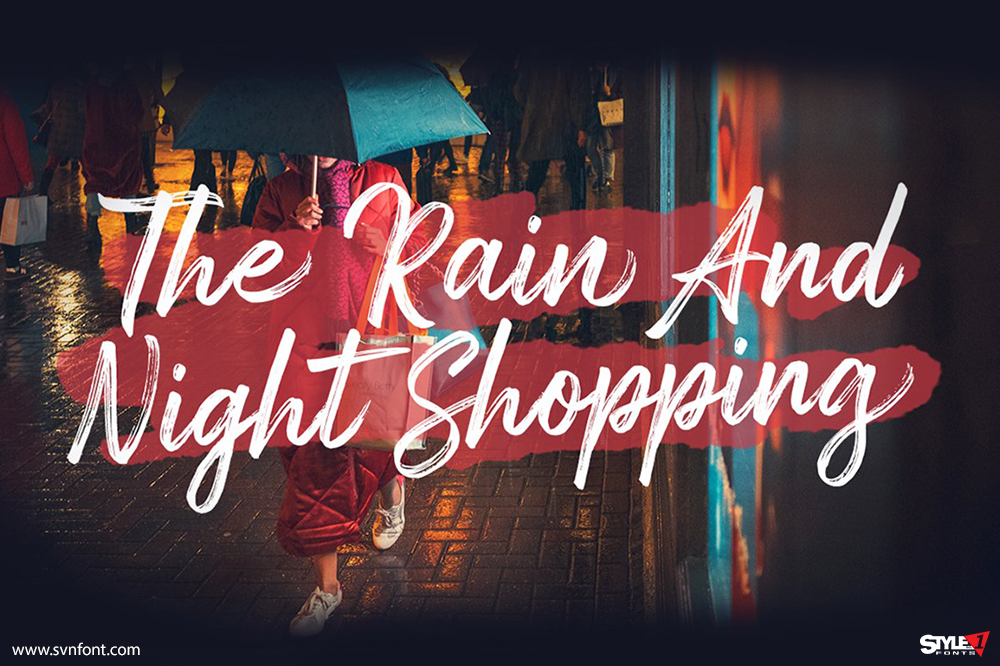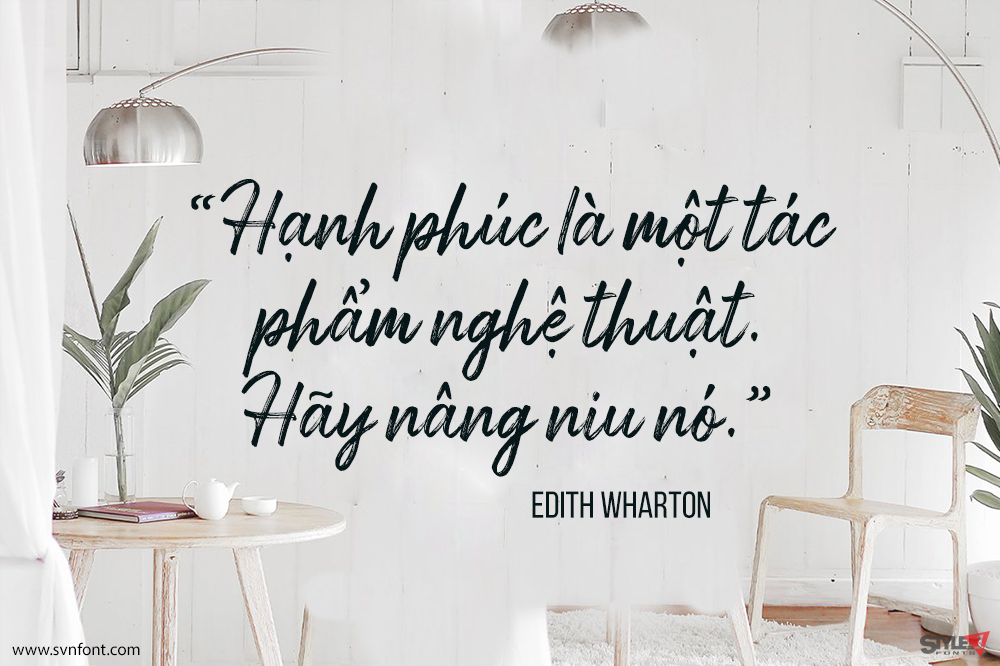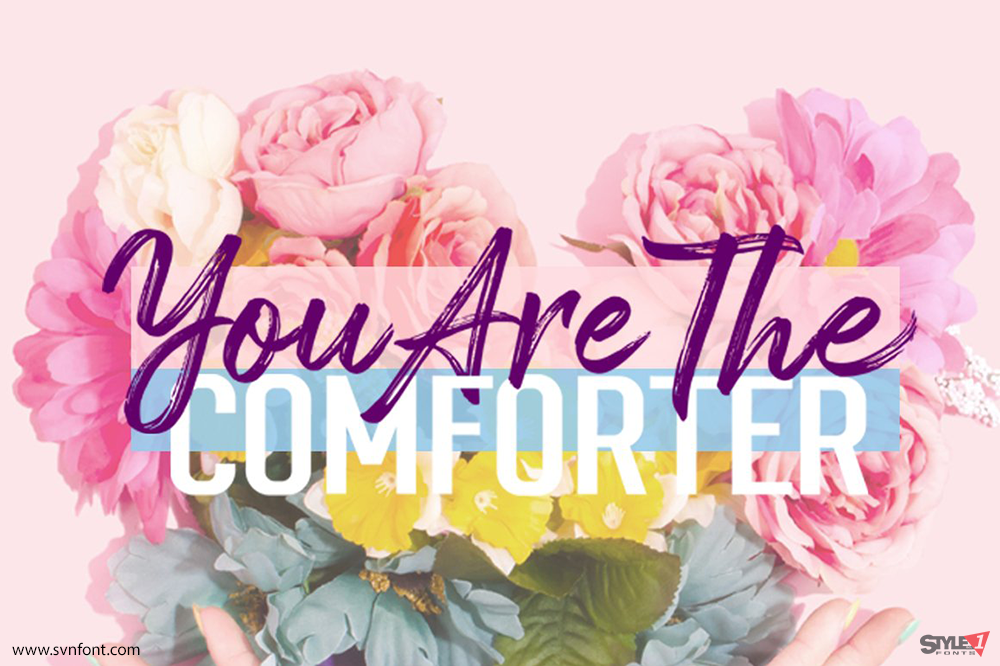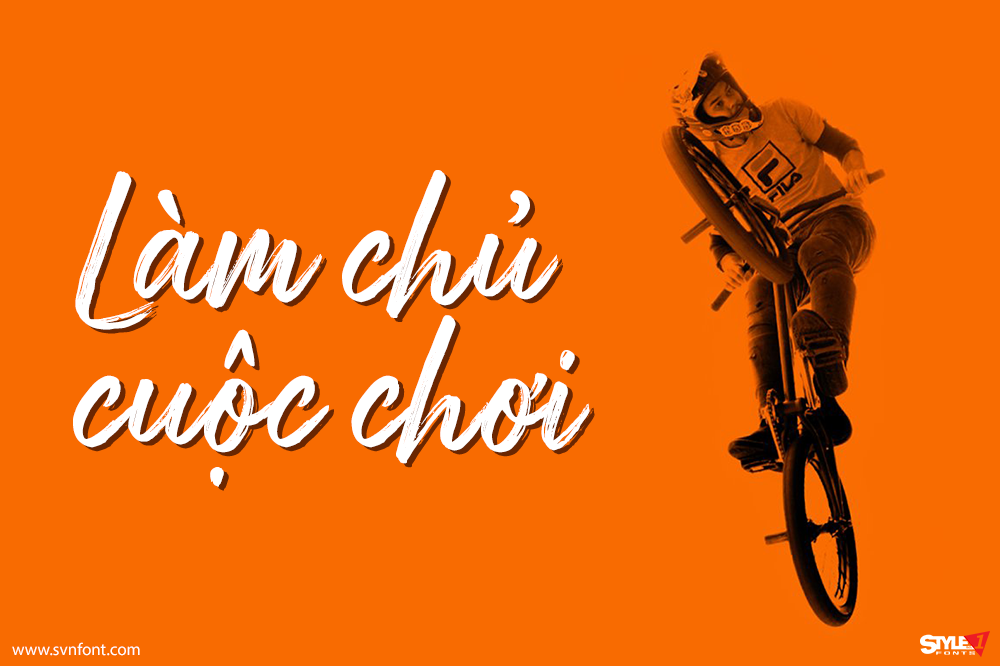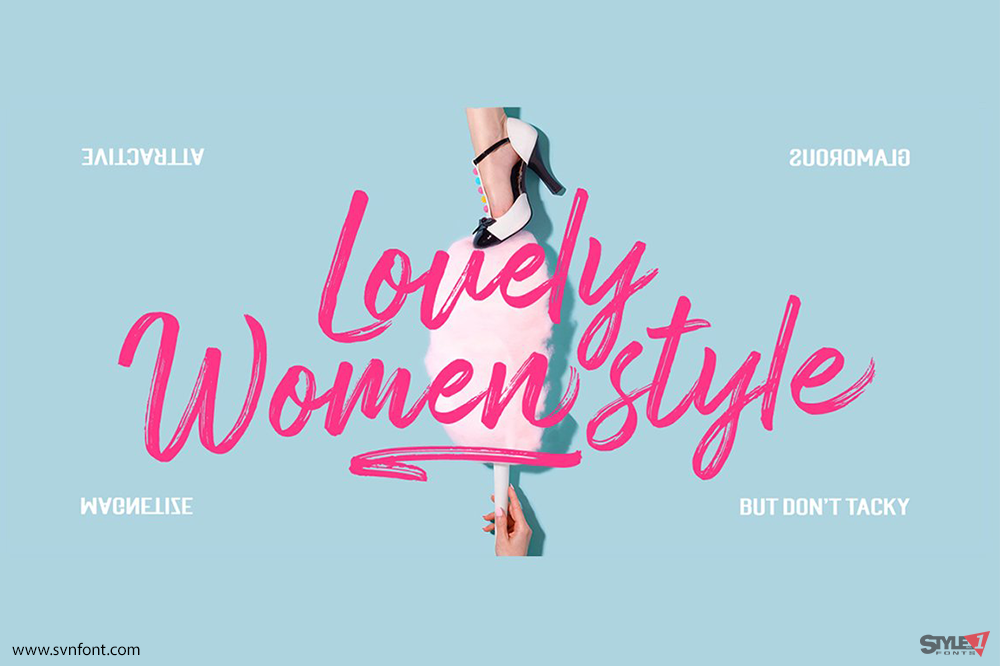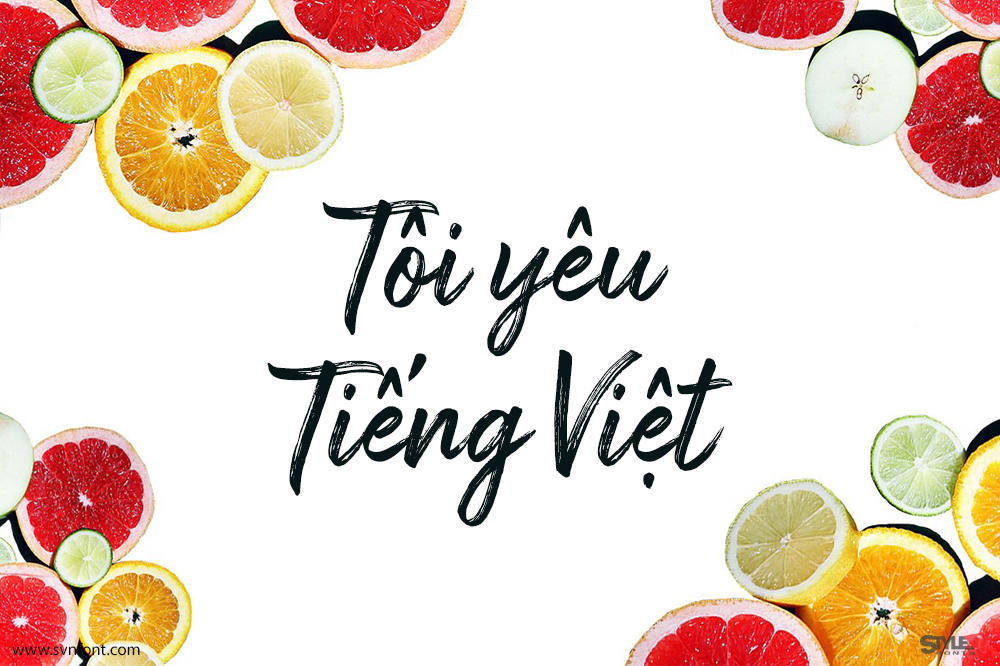
Arsilon là một font cọ vẽ, mang hơi thở đương đại với cảm giác thủ công tự nhiên. Font đi kèm underscores, cùng các ký tự thay thế (alternates) và ligature, giúp thiết kế của bạn trở nên sinh động và cuốn hút hơn.
Arsilon đặc biệt phù hợp cho thiết kế tiêu đề, như thời trang, thiệp mời, tiêu đề sách, văn phòng phẩm, quotes, branding, logo, thiệp chúc mừng, áo thun, bao bì, poster và nhiều ứng dụng sáng tạo khác.
Nhà thiết kế: Dhan Studio
Nhà phát hành: Dhan Studio